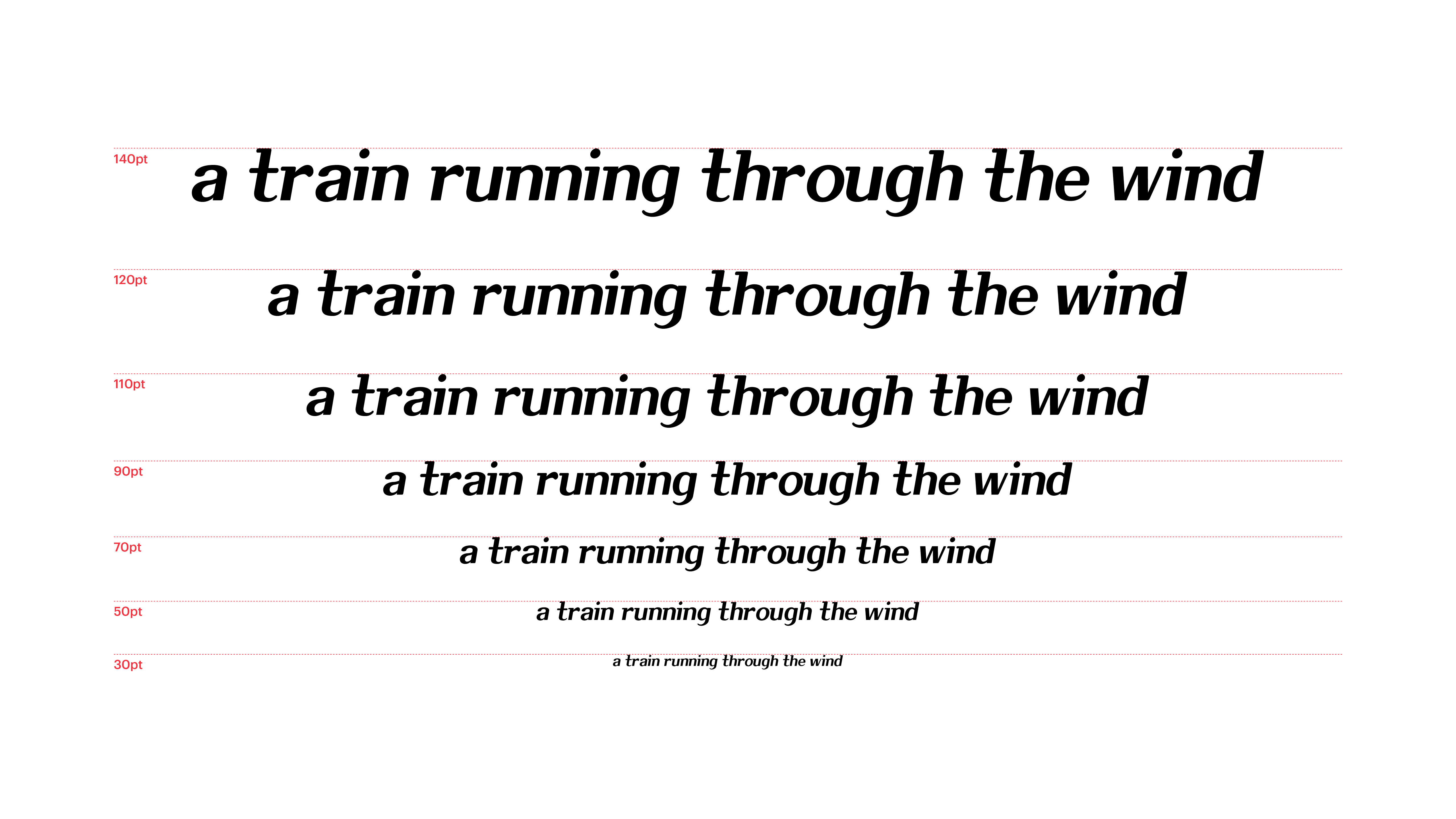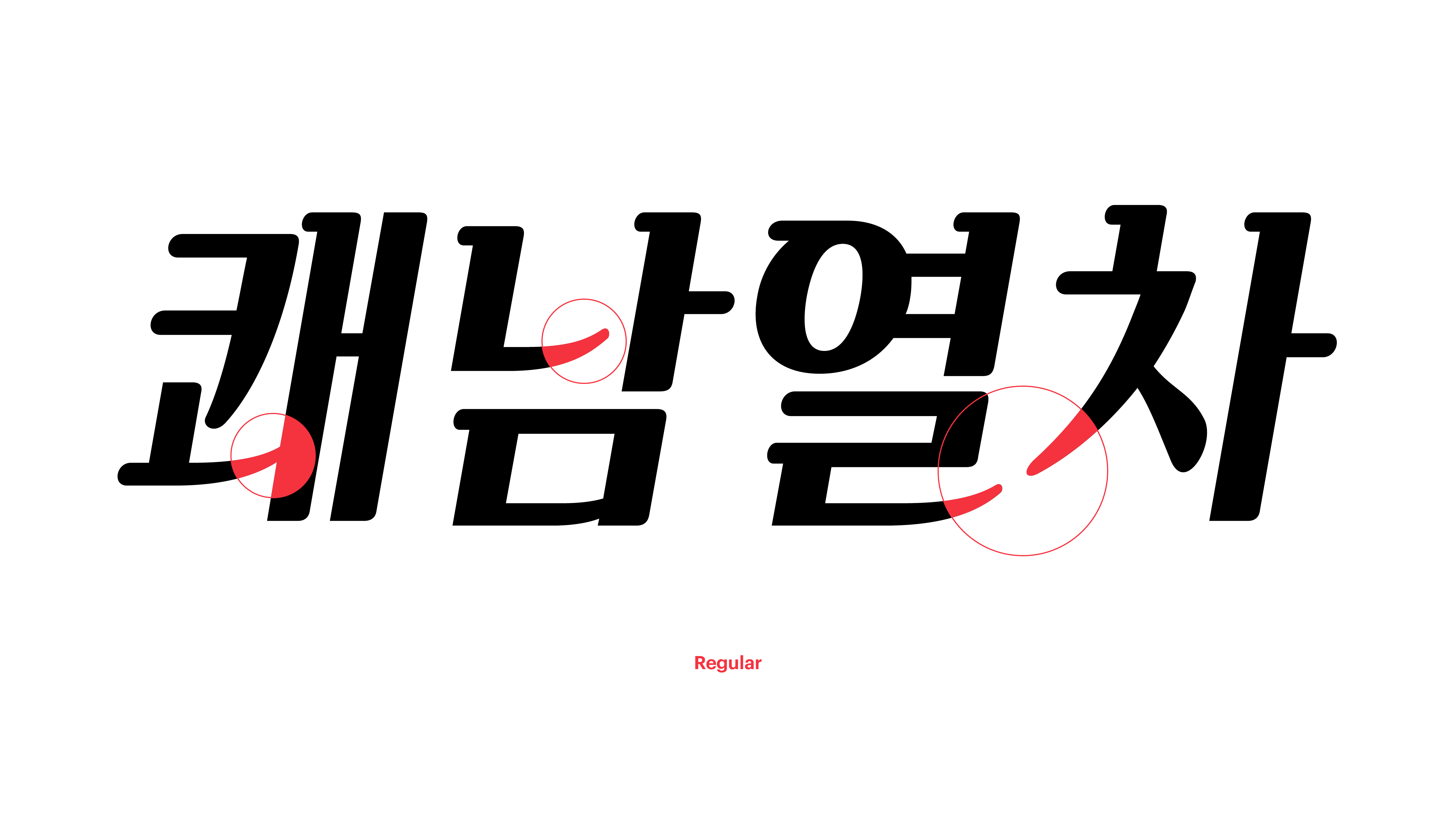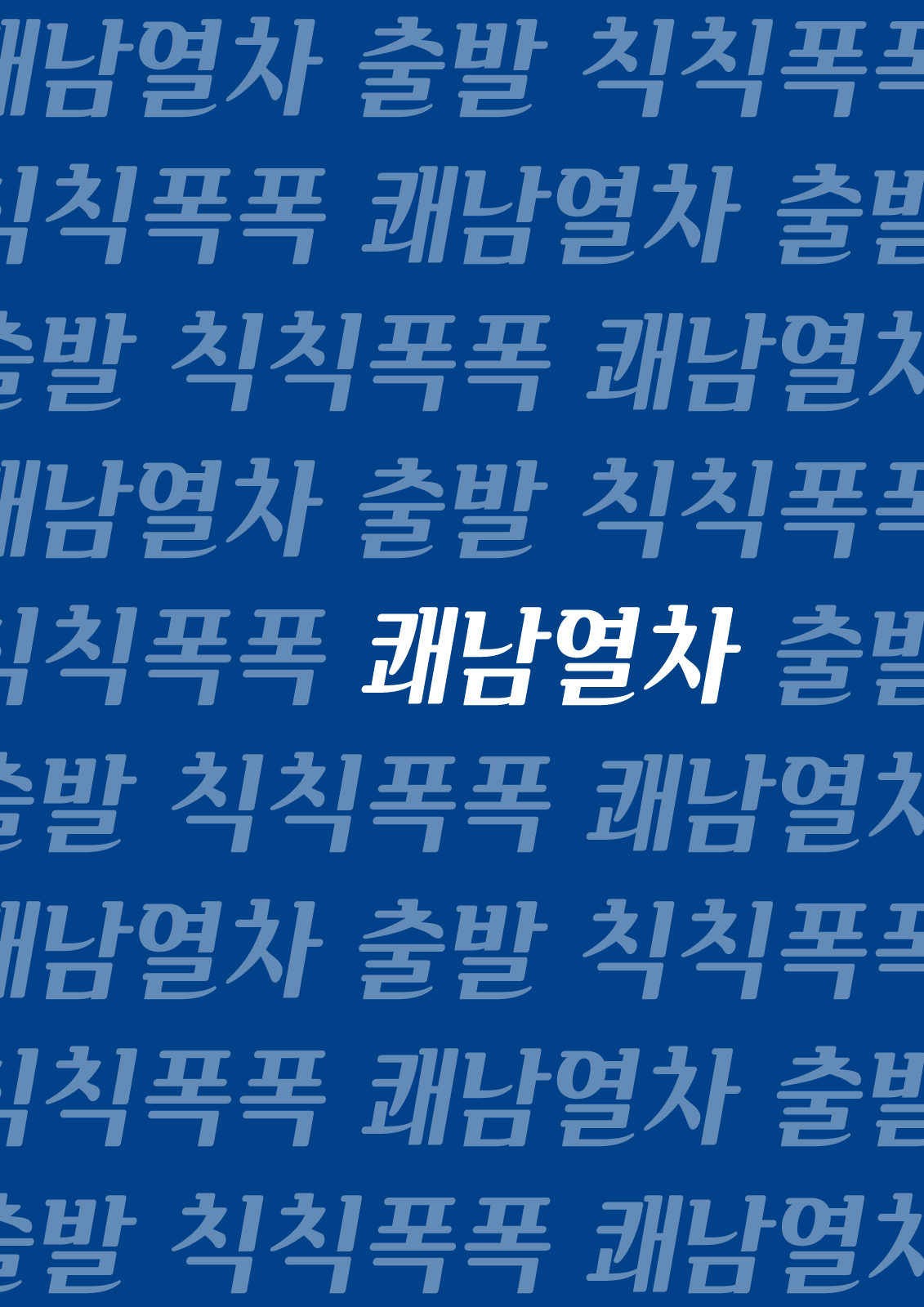
쾌남열차
Yoon 쾌남열차
바람을 가르며 달리는 열차의 생동감을 닮은 폰트입니다. 전체적으로 단단하지만 부드러운 곡선을 그리는 맺음 표현이 이 폰트의 매력 포인트지요. 수줍은 마음에 숨겨뒀던 내 매력을 유감없이 발산하고 싶을 때, 조금은 뻔뻔하게 쾌남열차체를 사용해보세요. 나의 장점을 100% 어필하는 거예요.